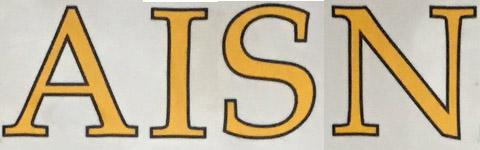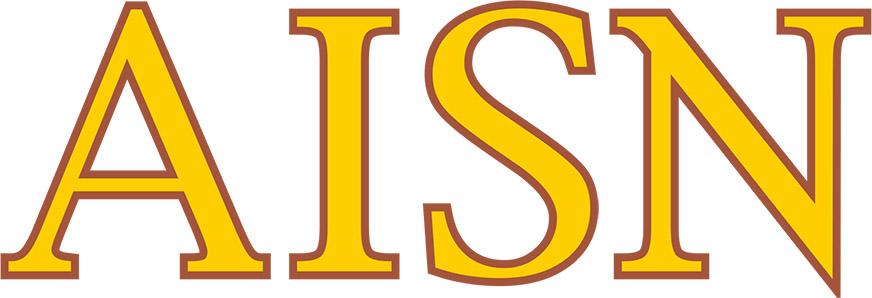
Älter wirkende Schrift ?
eventuell kann mir hierbei jemand von euch auf die Sprünge helfen ?
Das erste Bild war vor Jahren mal aktuell und wurde auf dem zweiten Bild etwas "erneuert".. allerdings ist die Schriftart nicht mehr herausfindbar :-(